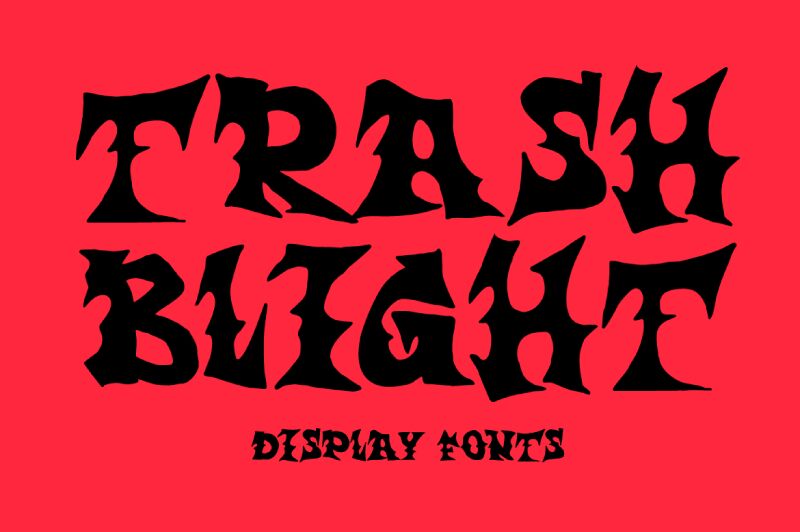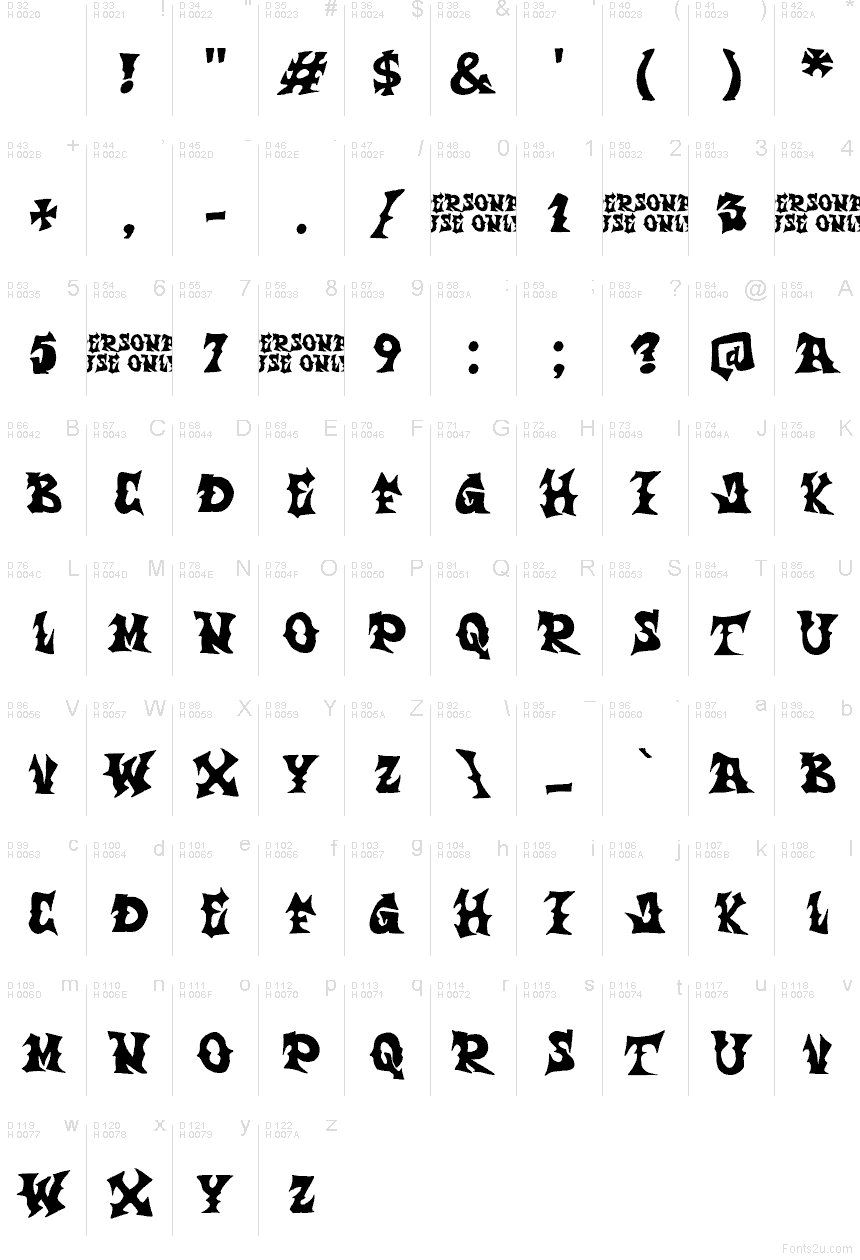
Trash Blight od Trash Fonts je bezplatné psychedelické nadpisové písmo s vydutými, ostře sevřenými tvary písmen. Jeho nepravidelné obrysy přecházejí mezi širokými křivkami a úzkými hroty a vytvářejí zkreslenou siluetu, která připomíná undergroundovou hororovou grafiku. Tvary působí, jako by byly ručně vyřezané a pokřivené.
Plakáty jsou jeho nejsilnějším médiem, zejména pro noční hororové akce, hlučné hudební vydání nebo netradiční filmové propagační materiály, kde se písmo může stát součástí uměleckého díla. Stejná zkroucená konstrukce se hodí také pro merchandising a herní grafiku, ale její nejvýraznější úloha je v titulcích filmů, které potřebují, aby nápisy samy o sobě nesly zlověstný, nespoutaný vzhled.